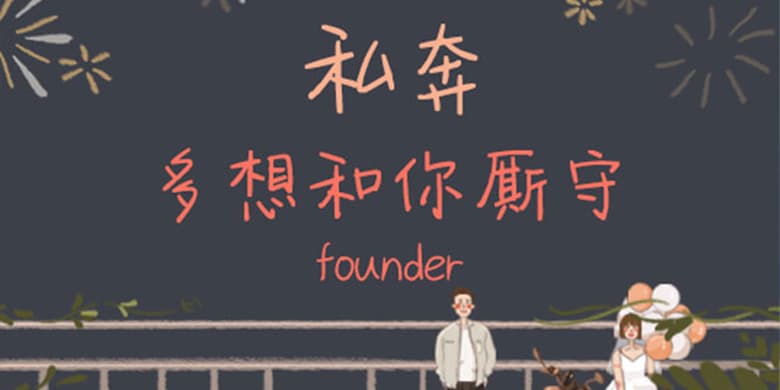
品牌:方正手迹设计师:刘晔发行时间:2020字库编码:大陆简体(GB2312-80)分类:创意书写字体属性:精品字
私奔这款字部件线条简洁,笔画排列打破常规横平竖直,横笔画多倾斜。字体整体给人感觉略带稚气又非常可爱,富有趣味性。适用于少年儿童类的书刊、品牌广告和产品包装设计,以及社交网络的个性化用字。